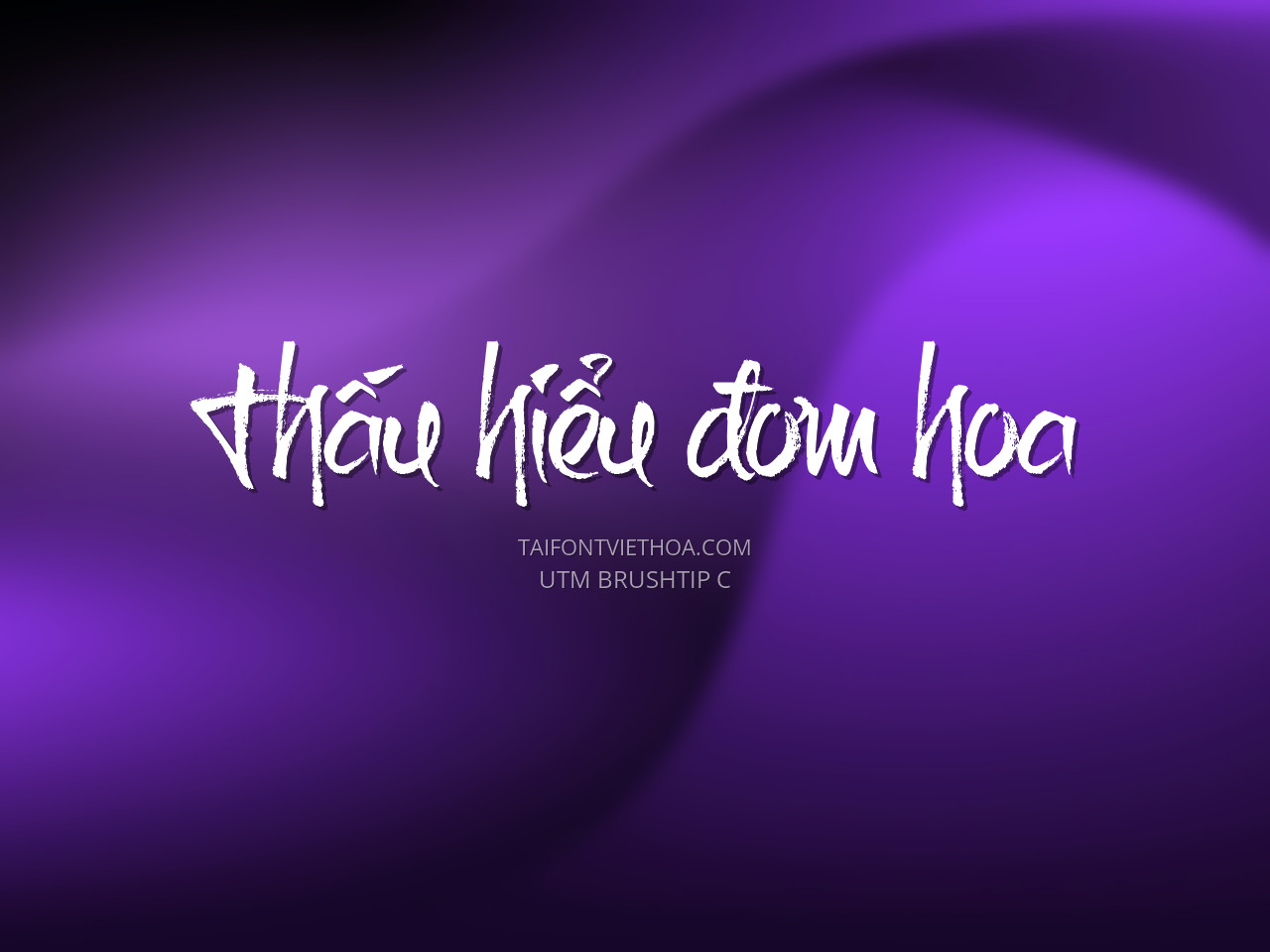
Font việt hóa UTM Brushtip-C
Giới thiệu về font UTM Brushtip-C
UTM Brushtip-C là phiên bản Việt hóa của font Brushtip-C – một kiểu chữ brush script độc đáo, mang phong cách viết tay mạnh mẽ và năng động. Font gốc được thiết kế với các nét cọ tự nhiên, tạo cảm giác sống động và đầy sáng tạo, rất phù hợp cho các dự án thiết kế cá nhân hóa và nghệ thuật. Phiên bản Việt hóa đã được hoàn thiện để hỗ trợ đầy đủ tiếng Việt cùng hơn 100 ngôn ngữ khác, giúp mở rộng khả năng sử dụng trong các dự án sáng tạo và truyền thông đa dạng.
Đặc điểm thiết kế và ứng dụng của UTM Brushtip-C
UTM Brushtip-C sở hữu cấu trúc brush script với các nét cọ dày, mềm mại và đậm chất nghệ thuật. Font có các đường nét tự do, tạo cảm giác chuyển động và năng lượng, rất phù hợp cho các thiết kế mang phong cách cá nhân và sáng tạo. Font còn được trang bị nhiều ligature và glyph giúp tăng tính linh hoạt trong thiết kế.
Font phù hợp sử dụng trong các dự án thiết kế thiệp cưới, thiệp mời, poster nghệ thuật, logo thương hiệu mỹ phẩm, bao bì sản phẩm thủ công và các dự án truyền thông cá nhân hóa cao. Ngành nghề phù hợp gồm: tổ chức sự kiện, thời trang, làm đẹp, nghệ thuật sáng tạo, quảng cáo cá nhân hóa và thiết kế nội thất.